칼스버그 리브랜딩 : 새로운 잎사귀를 틔우다
칼스버그는 주요 경쟁사의 상당수가 브랜드 고급화 및 표준화를 추진하고 있는 모습을 보고 자신이 시장에서 뒤쳐지기 시작했다는 것과 회사의 맥주 제품군들의 브랜드 디자인에 일관성이 부족하다는 사실을 깨닫게 되었다. 이에 소비자에게 언제 어디서나 일관된 브랜드 이미지를 전달해주고, 각 하위 브랜드 제품이 모체 브랜드와의 연계성을 잃지 않으면서도 자신만의 가치를 표출해내는 브랜드 시스템을 개발해내는 것을 목표로 한 이번 프로젝트가 계획되었다.
칼스버그(CARLSBERG) 리브랜딩 : 새로운 잎사귀를 틔우다
J C 야콥슨(Jacobsen)은 자신이 개발해낸 칼스버그 효모를 독점하지 않고 전 세계에 나누어 주었다. 야콥슨은 맥주의 끝없는 발전을 원했고, 이를 위해 루이스 파트뢰르(Louis Pasteur), 알렉산더 플레밍(Alexander Fleming) 등 당대의 저명인사들과도 협력했다. 현존하는 라거(lager) 맥주의 대부분이 결국 그 역사를 거슬러 올라가보면 야콥슨이 발견하고 나누어주었던 효모에서 탄생했다고 할 수 있다.
이제는 라거 시장에서 수많은 경쟁사들을 상대해야 하는 상황에 놓인 칼스버그는 주요 경쟁사의 상당수가 브랜드 고급화 및 표준화를 추진하고 있는 모습을 보고 자신이 시장에서 뒤쳐지기 시작했다는 것과 회사의 맥주 제품군들의 브랜드 디자인에 일관성이 부족하다는 사실을 깨닫게 되었다. 이에 소비자에게 언제 어디서나 일관된 브랜드 이미지를 전달해주고, 각 하위 브랜드 제품이 모체 브랜드와의 연계성을 잃지 않으면서도 자신만의 가치를 표출해내는 브랜드 시스템을 개발해내는 것을 목표로 한 이번 프로젝트가 계획되었다.
※ 택시 스튜디오와 칼스버그의 프로젝트 주요 담당자들이 프로젝트 진행과정을 단계별로 설명한다.
01 — 브랜드 상징
스펜서 벅: 칼스버그는 세계에서 가장 유명한 브랜드 중 하나로 168년의 역사를 지니고 있다. 우리의 최우선 목표는 칼스버그 맥주 제품군들의 디자인에 일관성을 부여하는 것이었고, 칼스버그 브랜드의 고급스러운 가치와 전통을 담아낼 수 있는 방법을 찾아내는 것은 이번 프로젝트의 핵심 과제였다.
02 — 효과적인 브랜드 연출
벤자민 호프만: 사람들은 무엇을 보고 칼스버그 제품을 알아보는가? 우리는 이 질문을 우리 스스로에게 던져보았다. 어떻게 하면 브랜드 디자인으로 우리의 이야기를 가장 효과적으로 전달할 수 있을까? 우리는 위대한 유산과 배경을 지니고 있지만, 어떤 시장은 그런 것들에 전혀 관심을 보이지 않을 수도 있다는 것에 주목했다.
03 — 브랜드 상징성
스펜서 벅: 우리는 기존의 홉 잎사귀 상징을 핵심 모티프로 사용하고, 이를 브랜드 전면에 내세우는 방안에 대해 연구했다. 연구를 통해 홉 잎사귀 무늬가 지닌 가능성을 확인할 수 있었고, 중요 하위 브랜드 엘리펀트(Elephant)에 완벽하게 어울리는 브랜드 디자인이 만들어지게 되었다. 엘리펀트의 디자인은 모든 하위 브랜드 디자인이 나아갈 방향을 제시해주었다.
04 — 깨달음의 순간
제시카 펠비: 모두가 알다시피 홉은 맥주의 주원료이다. 홉은 칼스버그 브랜드의 본질에 가까운 요소이며, 제품의 물리적 구성 성분이기도 하다. 깨달음은 엘리펀트 디자인 작업 과정 중에 찾아왔다. 그 순간 우리는 엘리펀트의 디자인 원리가 모든 하위 브랜드에도 적용될 수 있다는 것을 알게 되었다.
05 — 미래를 투영하다
스펜서 벅: 우리는 브랜드 마크의 표준화 및 현대화 방안에 대해 고민했다. 우리는 칼스버그의 50년 후의 모습을 상상해보고, 그 50년 후 미래의 모습으로 이어지는 발전 과정을 몇 단계로 나누어 구성해보았다. 흥미로운 접근 방식이었다.
06 — 디자인 탐구
스펜서 벅: 얼마 지나지 않아 분명해졌다. 우리 디자인은 나이키 로고만큼 강력하고 상징적인 디자인으로 진화해 나갈 수 있는 가능성을 지니고 있었다. 우리는 칼스버그 제품군들과 하위 브랜드들에 대해 조사하면서 홉 잎사귀 로고의 발전 방안에 대해 연구했다. 크기와 적용 위치 설정 등을 위한 과학적인 분석을 진행하고, 다양한 형태의 병마개 디자인을 시험해보았다.
07 — 색채 계획
조나단 터너-로저스: 칼스버그의 녹색은 세상의 모든 녹색 중에 가장 돋보이는 것이어야만 했다. 우리는 최대한 원색에 가까운 녹색을 포함해 다양한 색조의 녹색들을 시험해 보았다. 그리고 그것들이 어떤 의미를 전달해주는지, 사람들의 반응은 어떠한지에 대해 탐구했다. 우리는 청량감을 표현하기 위해 밝고 활기찬 색조의 녹색을 기본 바탕으로 어둡고, 풍성하고, 고급스러운 색조의 녹색들을 함께 사용했다.
08 — 타입 디자인
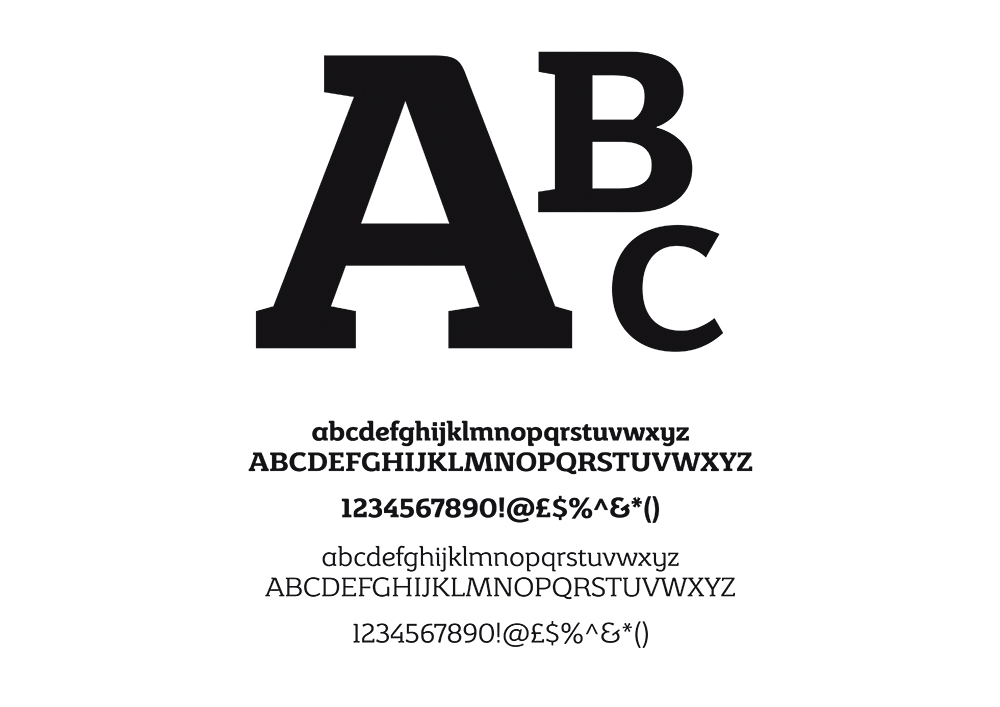
스펜서 벅: 칼스버그의 기존 타입에는 브랜드 핵심 가치가 투영되어 있지 않았다. 때문에 콘트라푼크트(Kontrapunkt)와 협업해 브랜드 대표성과 연계성을 지닌 타입을 새로 디자인했고, 새 타입이 칼스버그 브랜드 마크와 조화를 이루는 것은 물론, 독자적인 존재감을 드러내며 브랜드를 바로 연상시켜주는 시각적 요소로 작용하기 원했다.
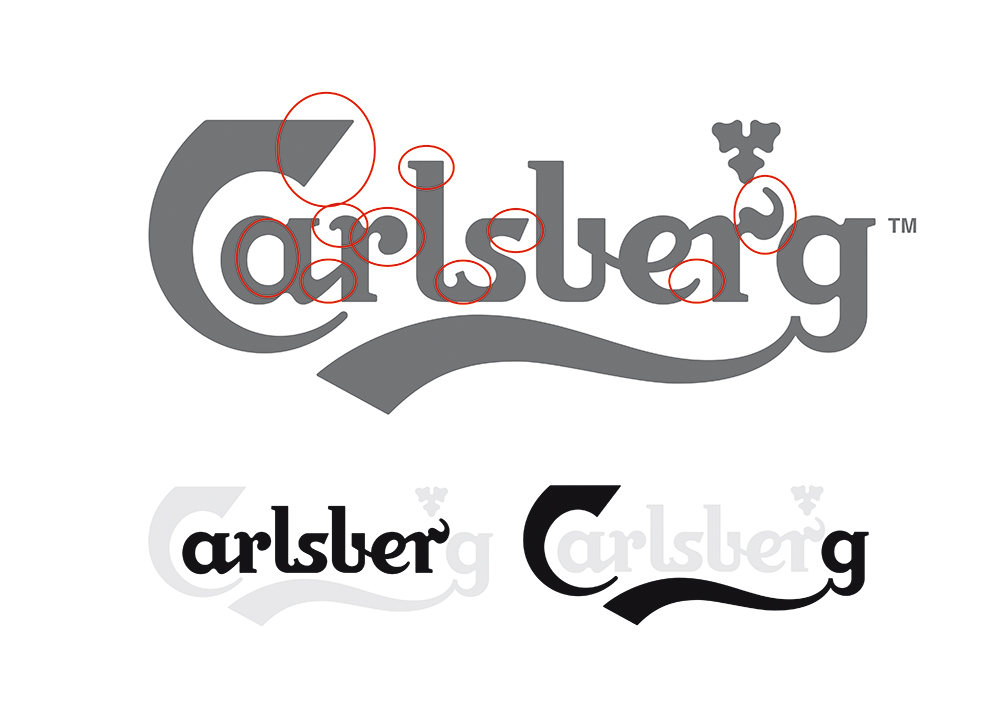
덴마크의 타입 디자인 전문 에이전시 콘트라푼크트와의 협업을 통한 타입페이스 개발
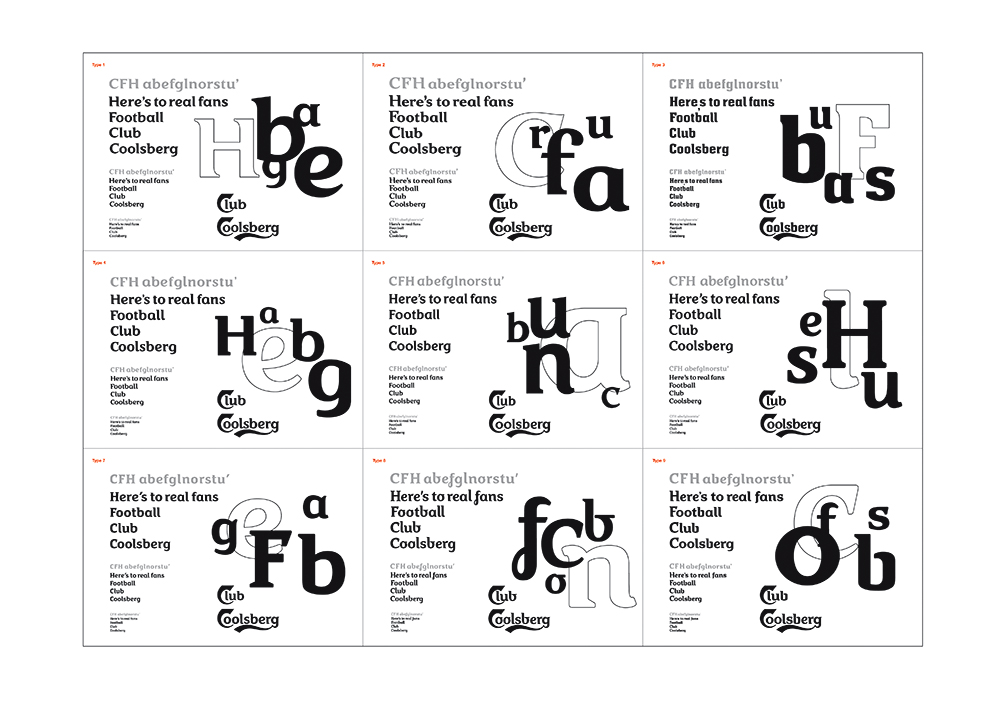
덴마크의 타입 디자인 전문 에이전시 콘트라푼크트와의 협업을 통한 타입페이스 개발
09 — 하위 브랜드 디자인 차별화
스펜서 벅: 하위 브랜드들은 여전히 자신의 독창적인 개성을 드러낸다. 일부 핵심 디자인 요소들을 보존시켜 소비자들이 자신이 가장 좋아하는 맥주를 바로 알아볼 수 있도록 했다. 반면, 홉 잎사귀 무늬는 이들이 칼스버그 브랜드에 귀속되어 있음을 확인해준다.